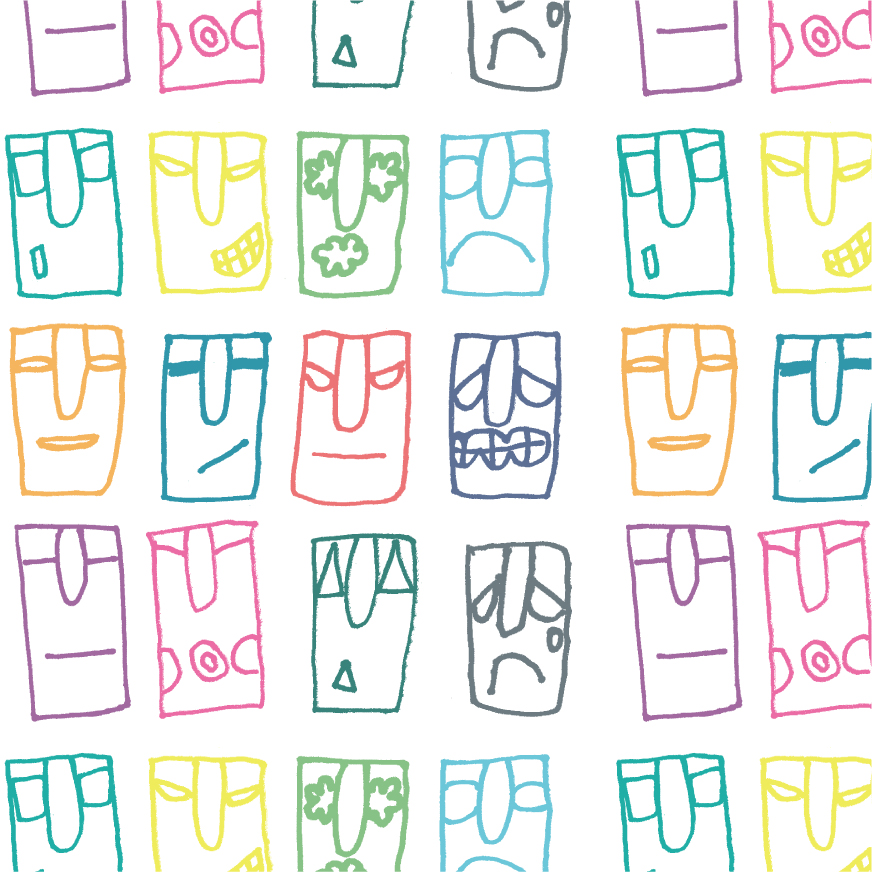
every day
渋谷モヤイ像は、新島から渋谷区へ寄贈した像で、新島では「モヤイ」とは、「協力する、助け合う」という意味だそう。アーティストの描くモヤイ像は、いろいろな表情をしていますが、どれも本人らしいおだやかな印象でした。たのしいとき、うれしいとき、かなしいとき、色々な時がありますが、「靄(もや)い」ながら毎日を、おだやかにすごしていきたいと思い、デザインしました。(曽志崎 望美)